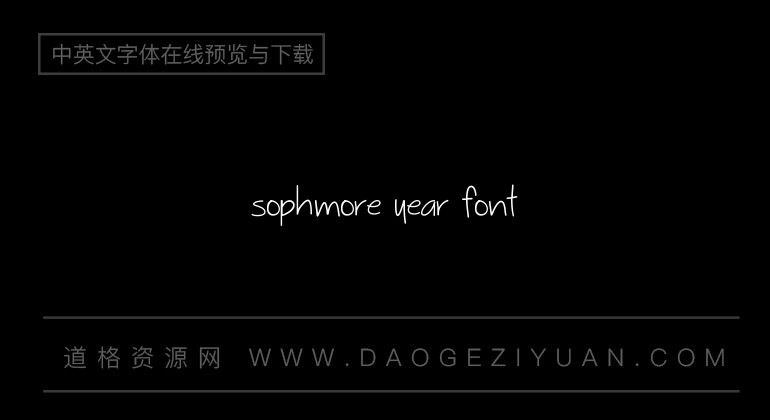
Sophomore Year Font 是一种时尚的手写字体,设计来自于美国匹兹堡的一位设计师,其主要特点是字母形态不规则,线条独特,非常适合用于海报、包装、广告等设计领域。 该字体有两种不同的风格:一种是默认的手写风格,另一种是使用了大写字母的版本,这种版本更适合于标题和标志等设计。 Sophomore Year Font 具有流畅的线条和自然的笔画,这使得它在设计中使用时可以提供独特的视觉效果,能够很好地吸引观众的注意力,是一种非常有吸引力的字体。内容介绍
Sophmore Year Font是一款非常不错的手写艺术字体,具有很好的视觉感,适合于文化类的宣传设计、商业类品牌的广告和产品包装设计以及个性化文字排版等较多场景。